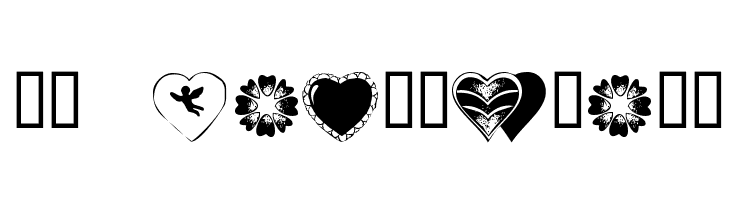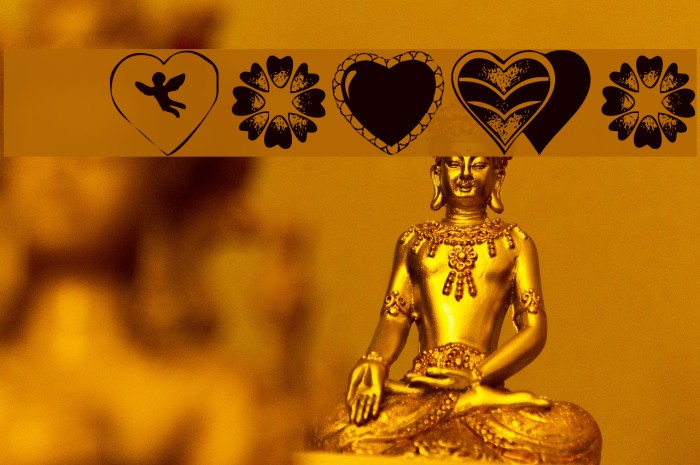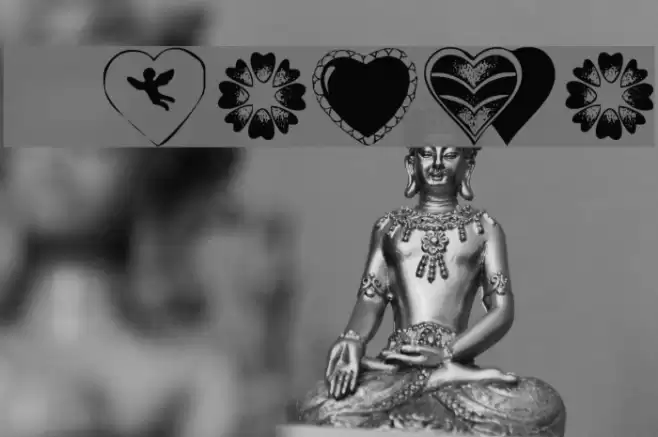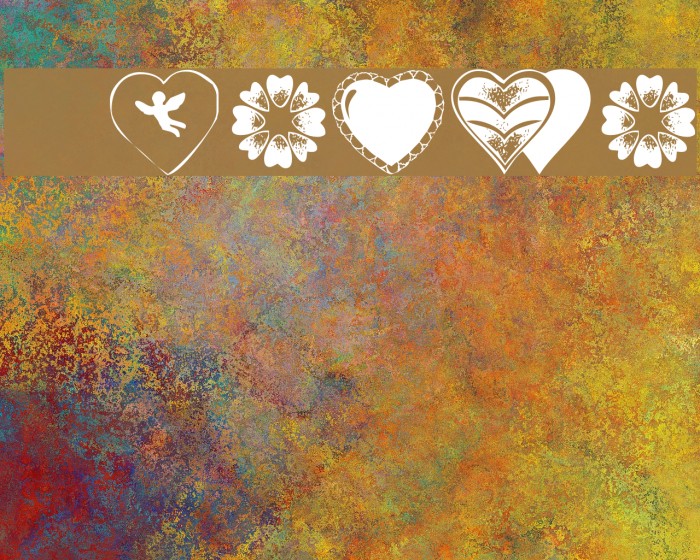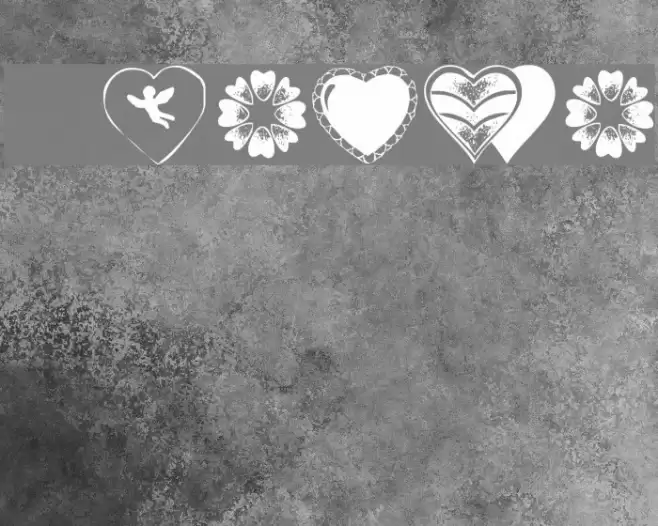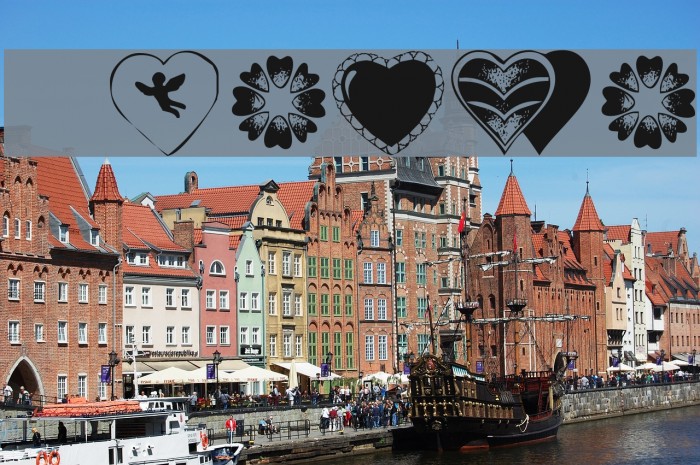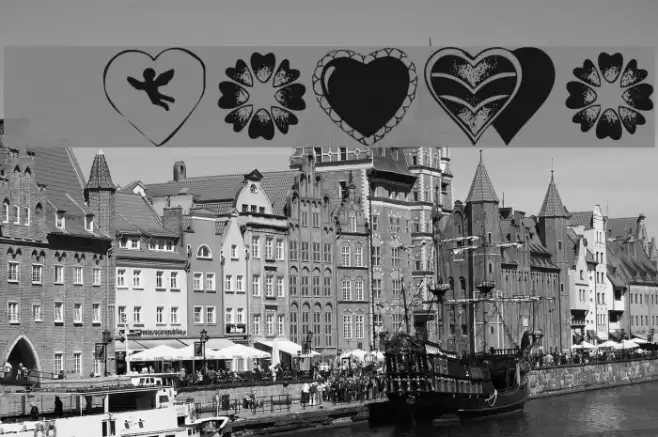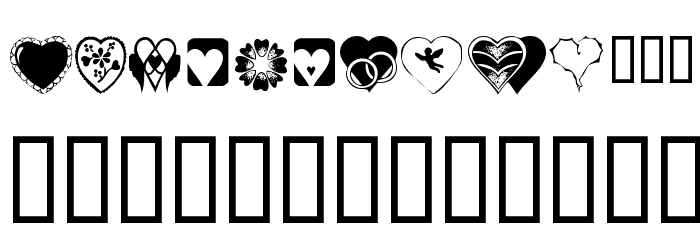
KR Heartiness Font
Cette police comprend 24 caractères. Cliquez sur un caractère pour voir les détails.
| Cas d'utilisation | Decorative elements, not suitable for text. |
| Projets proposés | These heart symbols can be used for decorative projects such as greeting cards, invitations, or digital art where a romantic or affectionate theme is desired. |